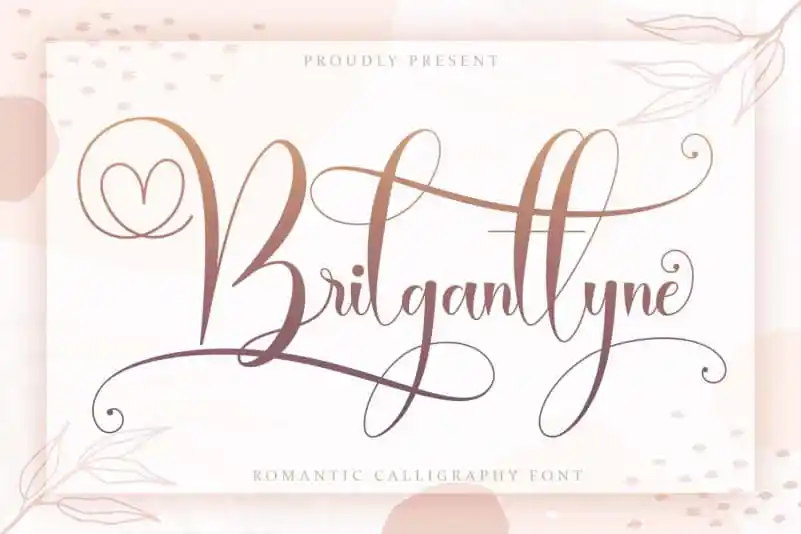
Brilganttyne Script Font – Download Grátis
A Brilganttyne Script Font é uma linda tipografia para calligrafia romântica perfeita para projetos diversos que valorizam o estilo elegante e a delicadeza do gênero. Seja para criar um novo logotipo, personalizar itens de casa, embalagens de produtos ou até mesmo cartões de presente, essa fonte artesanal traz uma dose extra de criatividade à sua produção. A Brilganttyne é perfeitamente adequada para qualquer projeto que busca a delicadeza e o charme da calligrafia. Seja em branding para marcasar produtos, designs para mugs e lembranças personalizadas, criação de cartões de visita, capas de livros, identidades de lojas, até mesmo para gráficos e até mesmo para rótulos – essa fonte atinge todos esses nichos com maestria. Além disso, ela se encaixa perfeitamente em qualquer projeto que necessite de um toque especial, seja ele uma publicação ou material impresso, marca de produto personalizado ou até mesmo um evento único. Com a Brilganttyne Script Font, você pode transformar seu design com um toque singular e distintivo, tornando-o ainda mais original e memorável. Seja qual for o projeto que escolher para usar essa fonte, ela certamente ajudará a realçá-lo de forma única, proporcionando uma experiência visual maravilhosa aos seus clientes ou consumidores.